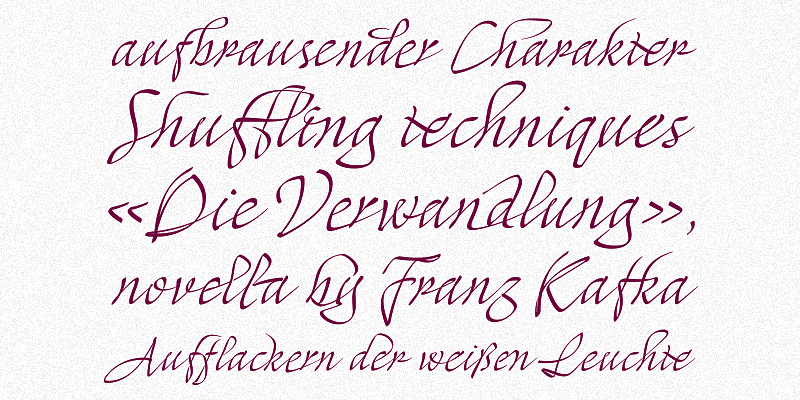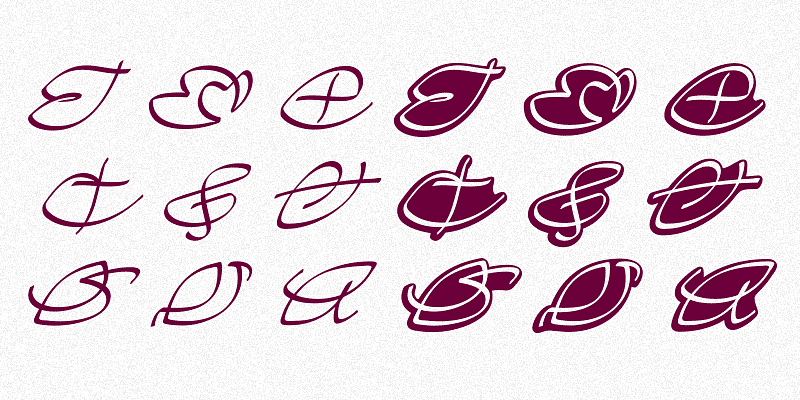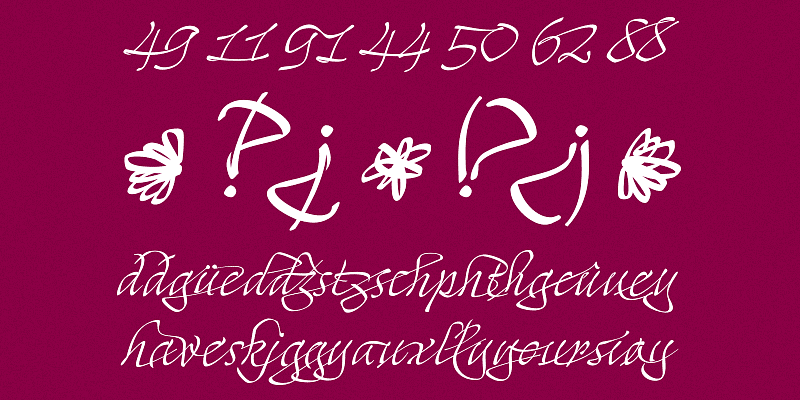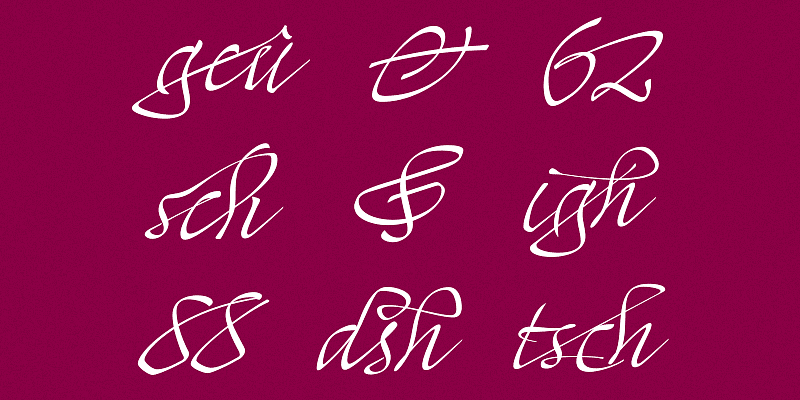
Mayence est une police manuscrite aux formes anguleuses et aux terminaisons en pointillés. La famille de polices contient plus de 400 ligatures, dont beaucoup sont faites pour plus de trois caractères joints et même quelques chiffres.